Dalam bidang bisnis wedding, style elemen visual seperti tipografi memiliki ciri dan karakteristik khas yang elegan, mewah dan lembut. Tipografi yang digunakan dalam desain wedding umumnya tidak akan dibuat terlalu tebal, kaku atau aneh karena tidak akan sesuai dengan pesan brand. Jenis bisnis wedding seperti make up artist, event organizer hingga fotografer seringkali memiliki gaya font elegan dan mewah yang sederhana.
Font wedding dalam berbagai desain logo, undangan, hingga konten akan memiliki visual yang sederhana dan elegan. Keterbacaan juga masih menjadi hal utama yang perlu diperhatikan agar menyampaikan pesan dengan baik. Pilih style font wedding yang sesuai kebutuhan dan tujuan desain agar menciptakan desain yang profesional.
PENGGUNAAN FONT WEDDING DALAM DESAIN LOGO
Dalam desain logo penggunaan font wedding yang elegan akan digunakan dengan hati-hati agar mudah dibaca dan merepresentasikan identitas merek dengan baik. Pastikan memilih gaya font yang tepat sesuai dengan jenis bisnis dan memiliki makna psikologi yang sesuai karakter bisnis. Style font wedding yang elegan dan lembut akan banyak digunakan untuk bisnis wedding seperti:
- Logo Wedding Organizer
- Logo MUA Wedding
- Logo Fotografer Wedding
- Logo Wedding Decor
KARAKTERISTIK FONT WEDDING
Style font yang biasanya sering digunakan dalam desain brand wedding banyak menggunakan gaya elegan. Tipografi yang digunakan harus merepresentasikan citra brand dan identitas brand. Secara umum, font untuk brand wedding sering memiliki karakteristik seperti:
Gaya Tipografi Kaligrafi atau Script
Font yang digunakan untuk desain brand wedding biasanya menggunakan font kaligrafi dan script. Gaya huruf tersebut akan memiliki goresan yang halus dan menyerupai tulisan tangan. Garis huruf juga memiliki lengkungan yang lembut sehingga memberikan kesan elegan dan personal.
Serif Klasik dan Elegan
Jenis font serif klasik tetapi bergaya elegan huga banyak ditemui dalam branding bisnis pernikahan. Desain pernikahan yang memiliki font serif klasik akan menciptakan visual yang mewah dan timeless. Biasanya gaya huruf serif akan memiliki huruf yang kontras tebal dan tipisnya. Ini sering digunakan untuk memberikan nuansa royal dan eksklusif.
Tipografi dengan Huruf Miring
Gaya huruf font wedding sering menggunakan style huruf miring agar menambah nuansa romantis dan elegan. Biasanya style huruf yang tipis dan miring akan efektif menciptakan kesan yang juga lembut. Tipografi akan tampil lebih anggun terutama ketika digunakan pada font serif dan script yang tipis.
Garis Tipis dan Elegan
Kebanyakan font wedding yang digunakan dalam desain brand wedding juga memiliki ciri utama garis tipis dan elegan. Seringkali garis tipis akan memiliki detail yang rapi sehingga font tampil bersih dan profesional. Hindari menggunakan font wedding yang terlalu tebal agar tipografi memiliki kesan ringan dan lembut.
Kombinasi Script dan Sans Serif
Untuk desain brand wedding, seringkali kombinasi font juga aja difokuskan pada style elegan, lembut dan sederhana. Misalnya kombinasi font script untuk nama pasangan dan font sans serif elegan untuk detail informasi. Kombinasi font tersebut akan menciptakan keseimbangan visual elegan dan keterbacaan yang baik.
Warna yang Lembut dan Feminim
Desain branding juga akan memiliki style warna yang lembut dan feminim untuk warna teksnya. Font desain brand wedding akan relevan dengan warna emas, warna pastel, putih atau soft pink. Hindari menggunakan warna yang mencolok atau cerah karena tidak semua tema wedding yang cenderung elegan.
REKOMENDASI FONT WEDDING YANG ELEGAN
Bisnis wedding umumnya akan memiliki karakteristik brand yang elegan, mewah, dan feminim, ini termasuk dalam penggunaan elemen visualnya. Elemen visual tidak hanya warna atau bentuk simbol, tetapi juga tipografi yang harus elegan. Berikut beberapa rekomendasi tipografi untuk digunakan dalam desain brand wedding agar elegan dan relevan:
Font Brongham Script
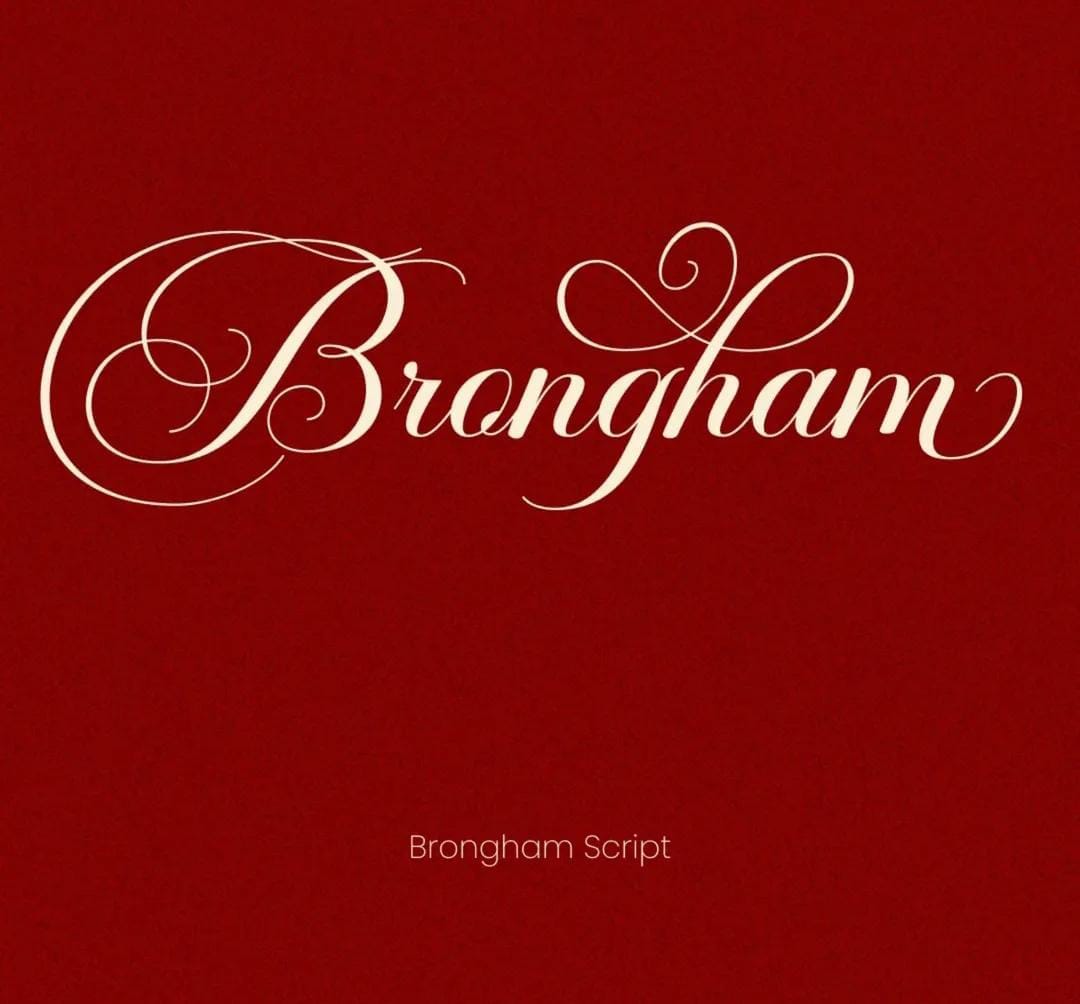
Jenis font script ini memiliki gaya huruf yang elegan, garis yang halus dan lembut sehingga bisa mencerminkan bisnis wedding dengan baik. Beberapa gaya huruf dalam font tersebut memiliki garis yang memanjang dan tipis. Kontras font script yang tipis dan tebal dalam tipografi tersebut menciptakan visual yang elegan.
Font script tersebut masih memiliki font yang mudah untuk dibaca dan bisa digunakan pada desain logo. Bisnis wedding organizer dan logo make up artis wedding akan cocok dengan menggunakan jenis font brongham script.
Font Morphidy Calligraphy Script
Kebanyakan font wedding juga memiliki gaya huruf miring agar font tampil semakin feminim dan elegan. Selain garis yang elegan, font tersebut memiliki ujung huruf yang melengkung terutama font yang memiliki ujung panjang. Gaya font tersebut dapat menciptakan desain brand yang lebih elegan.
Bisnis wedding biasanya akan memiliki karakteristik tipografi desain brand yang elegan, tipis, halus dan mewah. Gaya tipografi yang elegan akan relevan untuk merepresentasikan citra bisnis wedding. Penggunaan font wedding yang elegan akan banyak ditemui dalam desain logo MUA wedding, event organizer dan desain undangan.